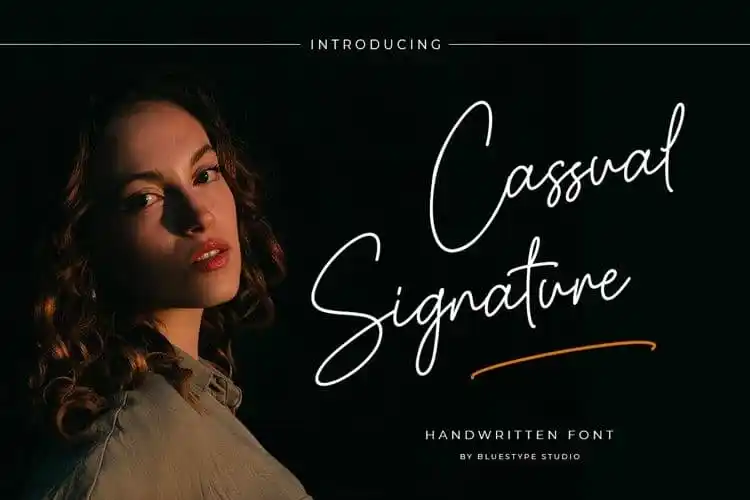
Cassual Signature Font – Download Grátis
A Cassual Signature Font é uma excelente opção para quem busca uma tipografia criativa e autêntica. Inspirada na escrita manuscrita com pequenas alterações nos deslizamentos rápidos de mão ou assinaturas, ela traz vida aos seus projetos mais imaginativos. Este script tem um toque suave e moderno que combina facilmente legibilidade com verdadeira personalidade, tornando-o ideal para aplicar em diversas áreas. A fonte Cassual Signature é perfeitamente adaptável a uma ampla gama de usos, desde criações fotográficas até editoriais. Ela é excelente para incorporar nas suas peças de moda ou em sua identidade visual, como business cards e mensagens criativas nos seus materiais de marketing, sejam eles t-shirts, logotipos ou água-marinha. Sua versatilidade permite que você inove em diversas formas de comunicação, desde assinaturas formais até criações ilustradas na moda e no design editorial. Adicione a Cassual Signature à sua paleta de ferramentas e veja como ela rediscerne suas ideias mais criativas. Este é um belo exemplo de tipografia que combina elegância com uma personalidade descontraída, tornando-a perfeita para as necessidades de design moderno em várias plataformas digitais e físicas.